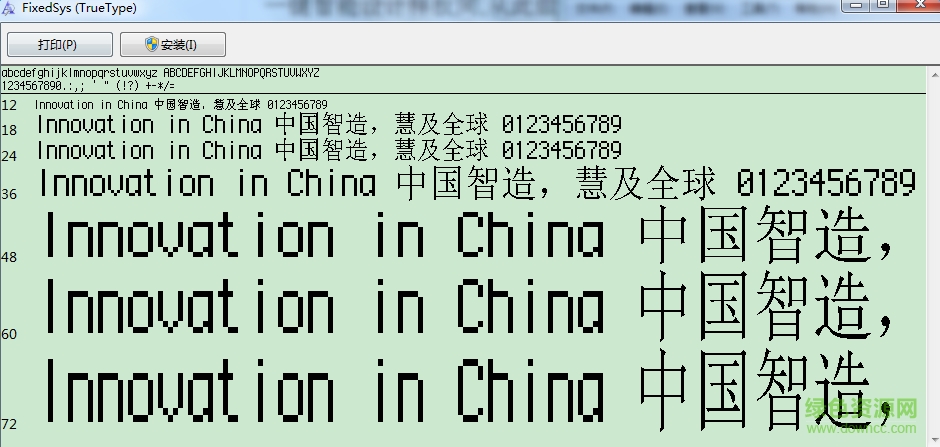
fixedsys.ttf是一款像素風(fēng)格的藝術(shù)字體,這款字體結(jié)構(gòu)簡(jiǎn)潔,易讀性強(qiáng),擁有較為完整的詞庫(kù),非常適用于ppt、影視制作、廣告設(shè)計(jì)、宣傳海報(bào)等領(lǐng)域,喜歡的朋友歡迎來(lái)綠色資源網(wǎng)下載使用。